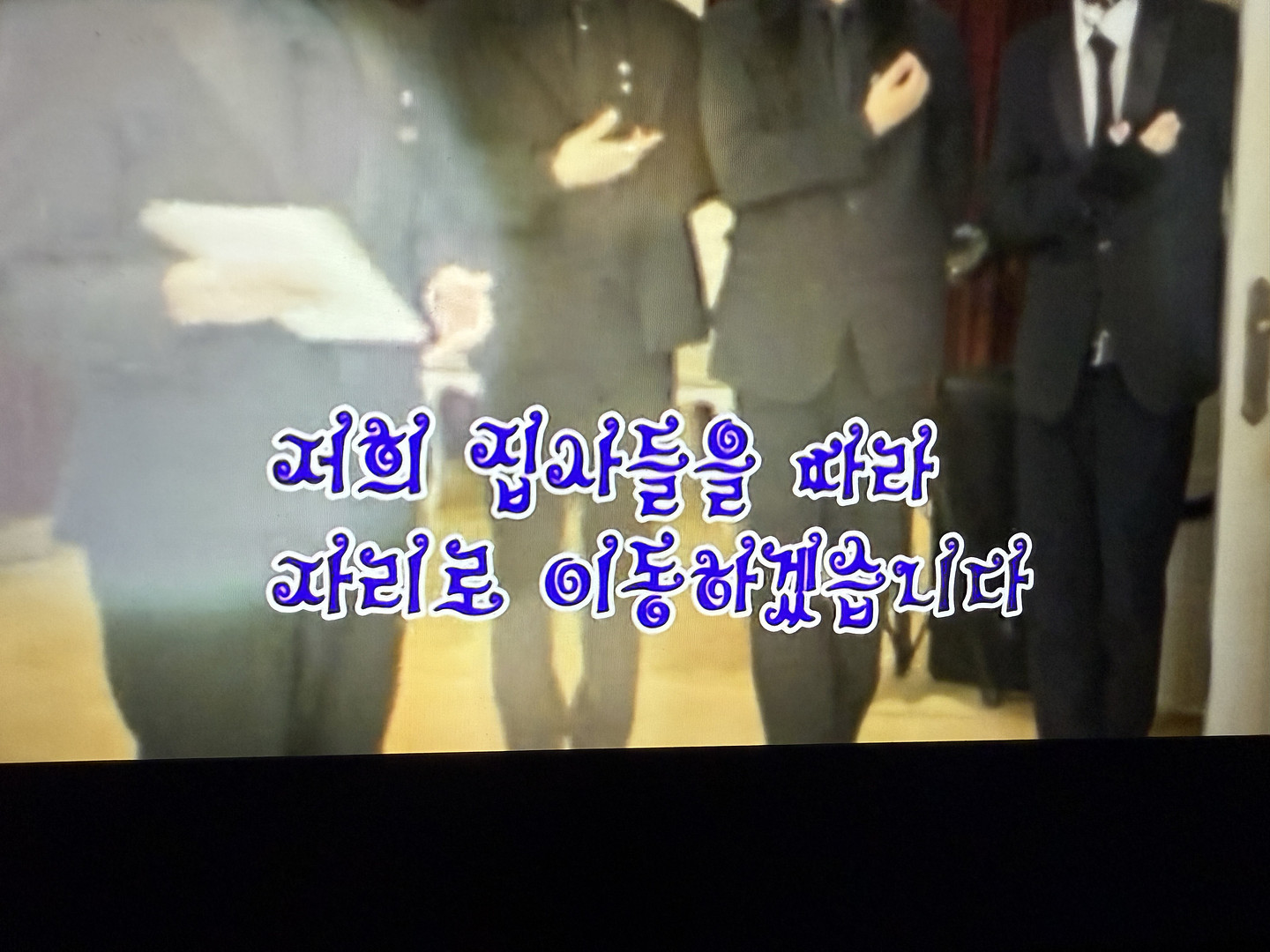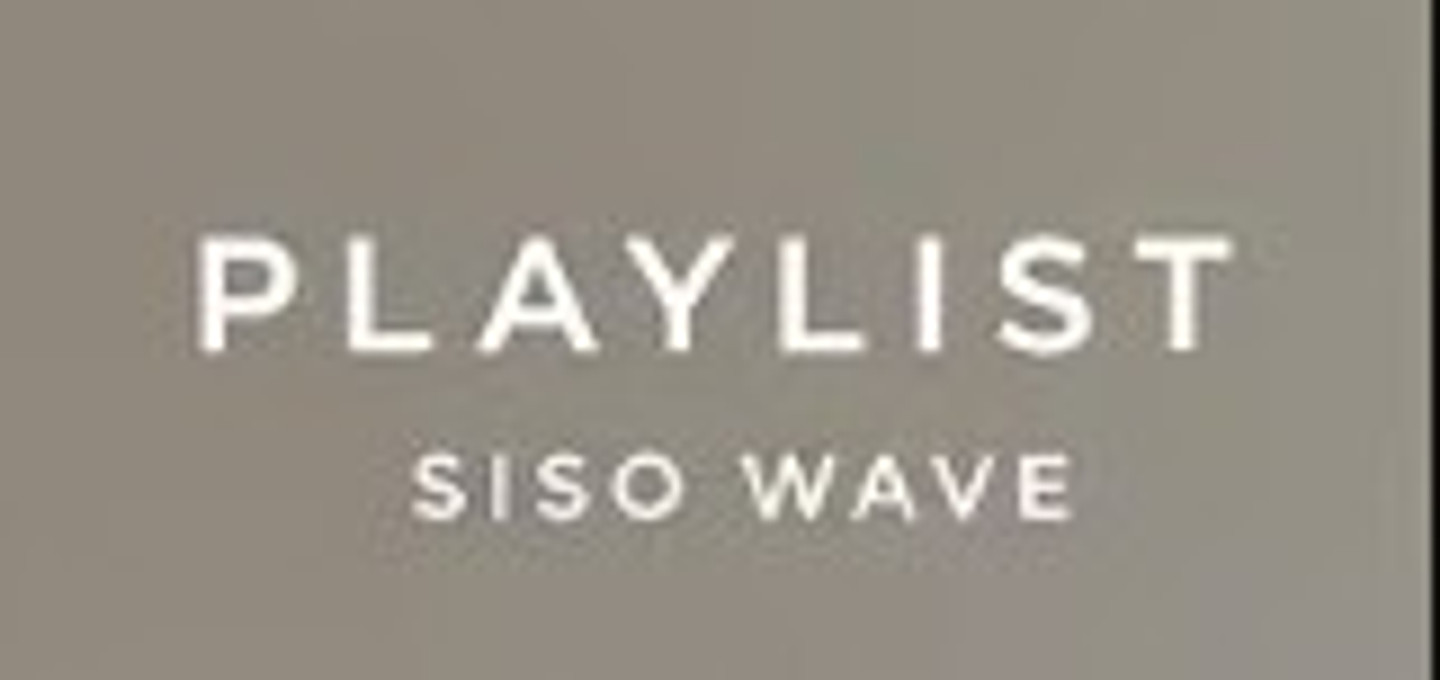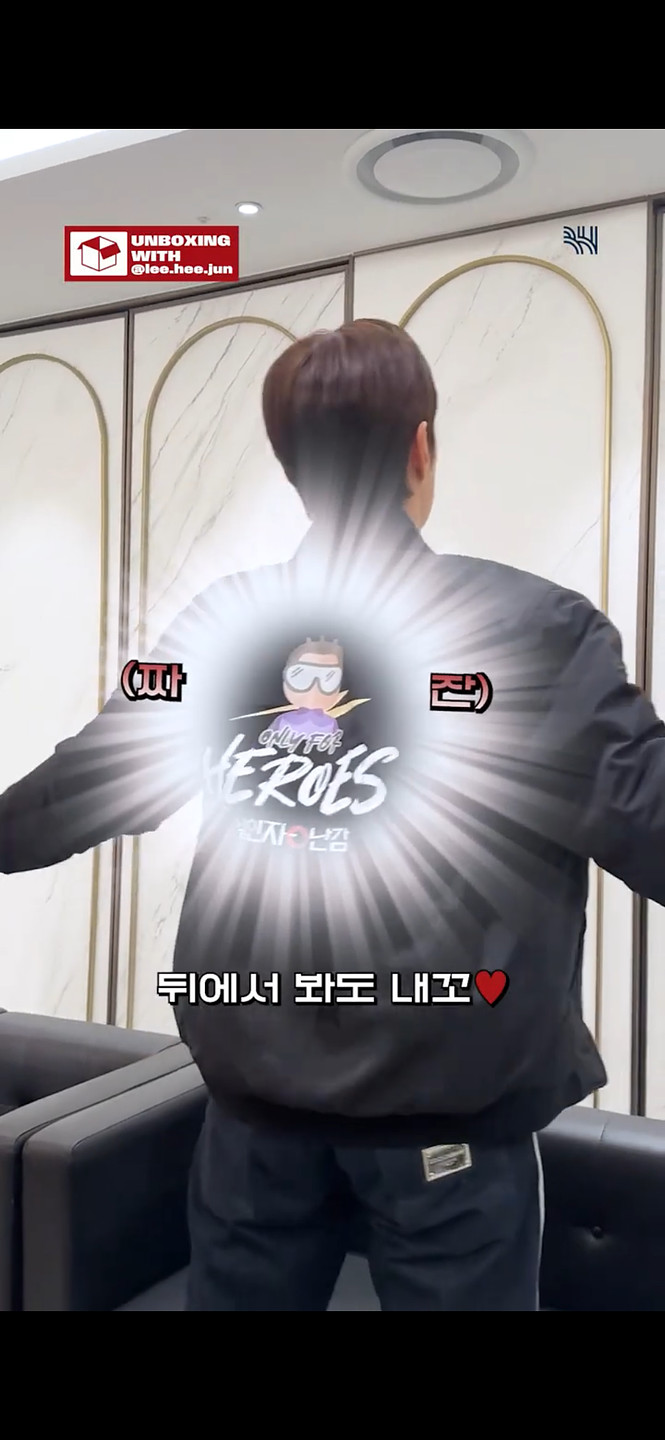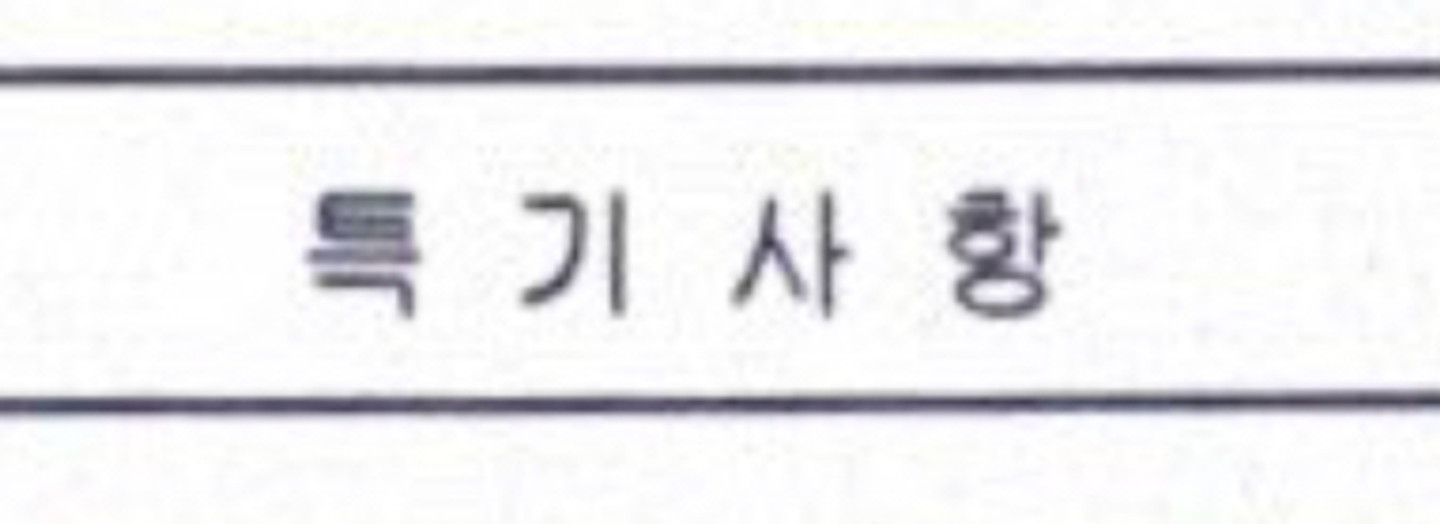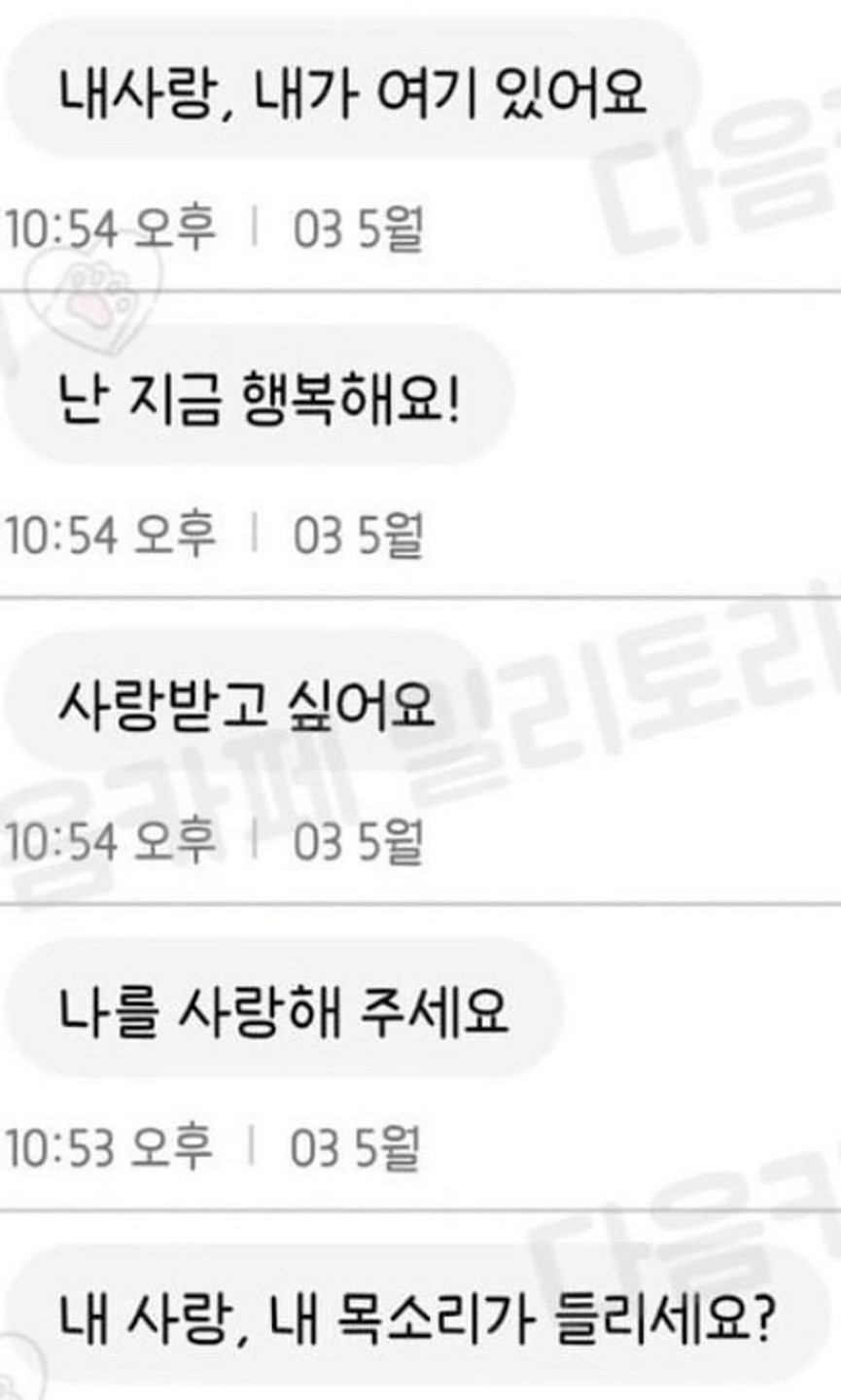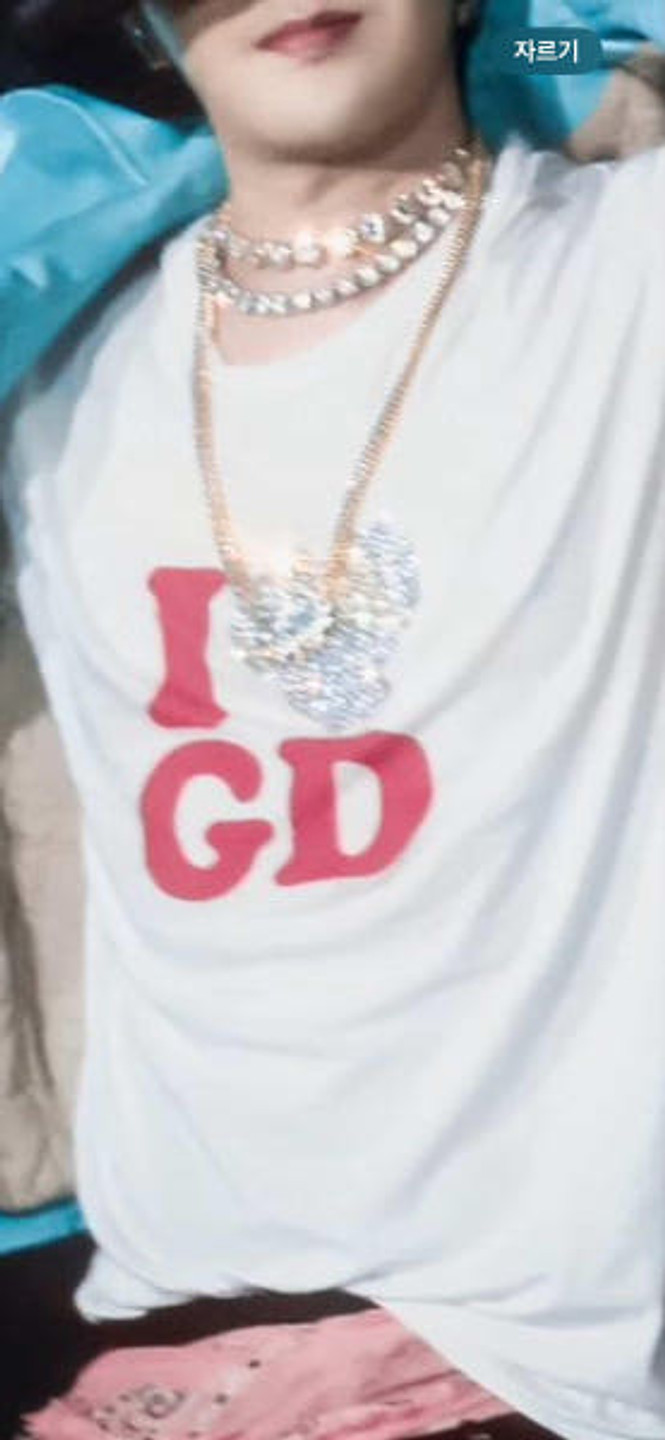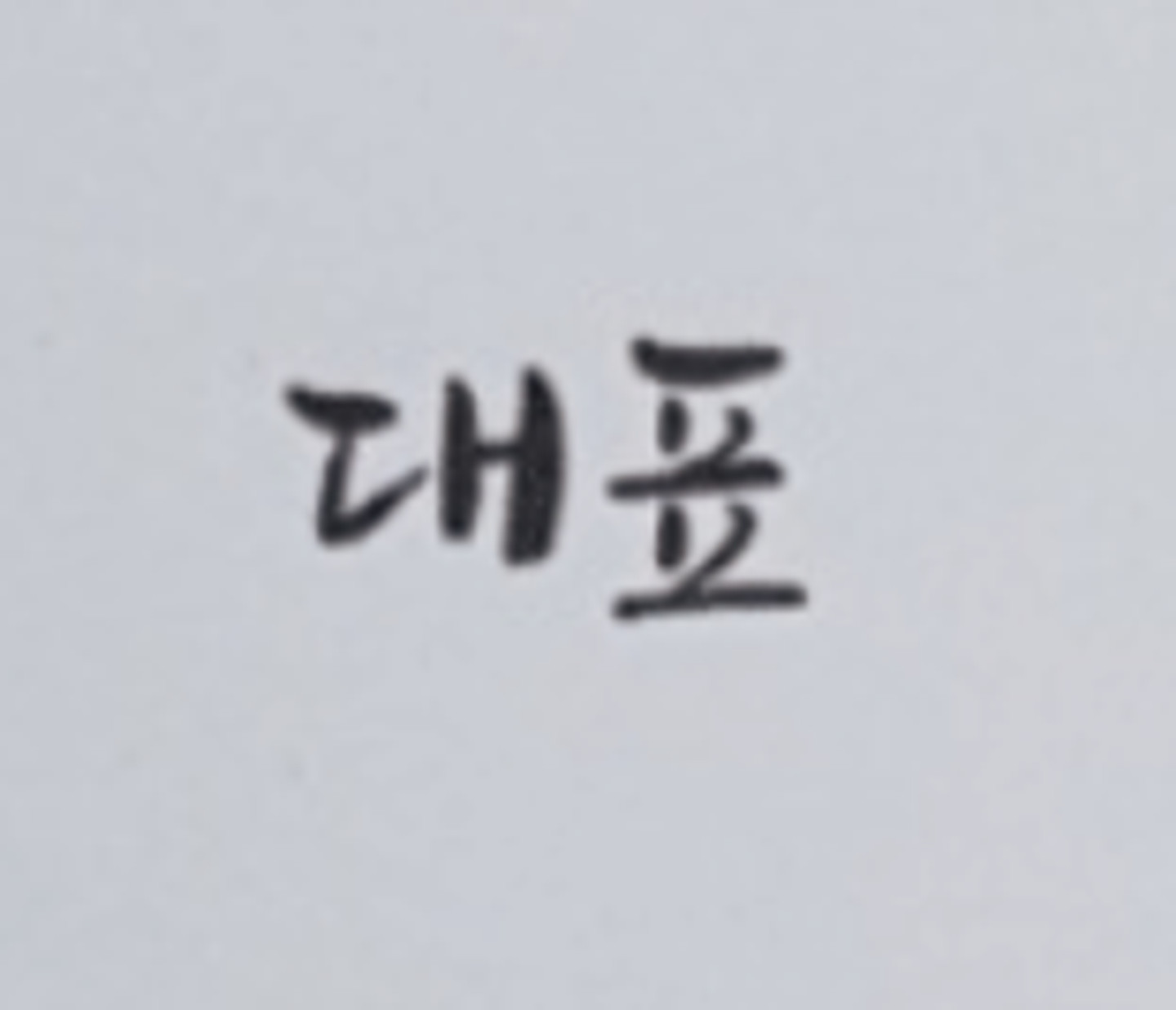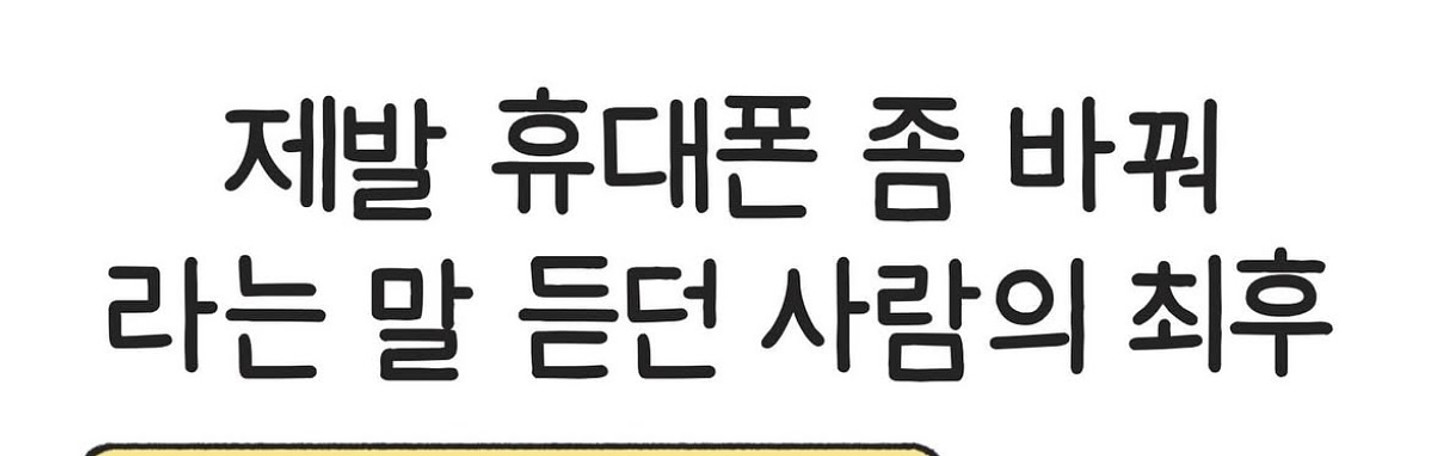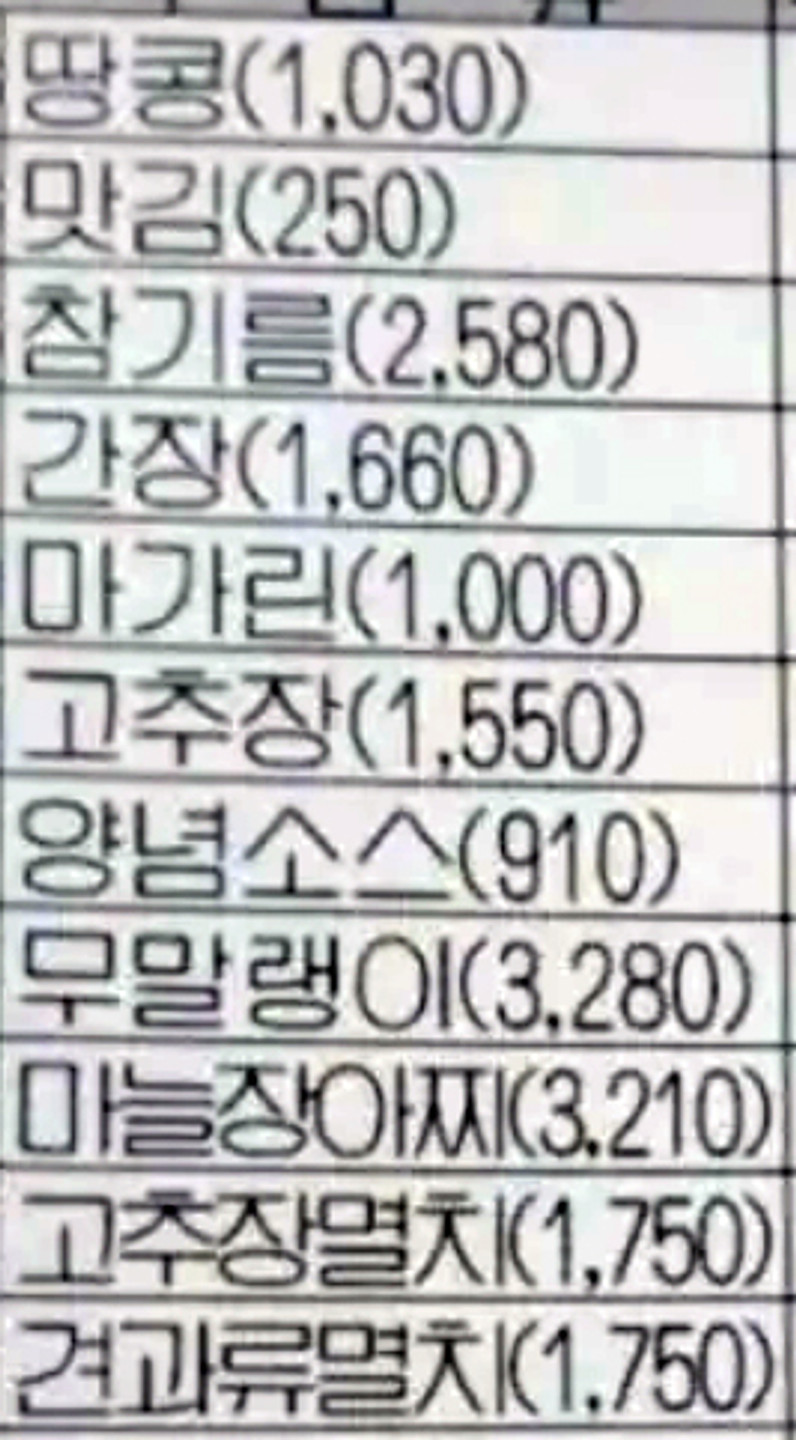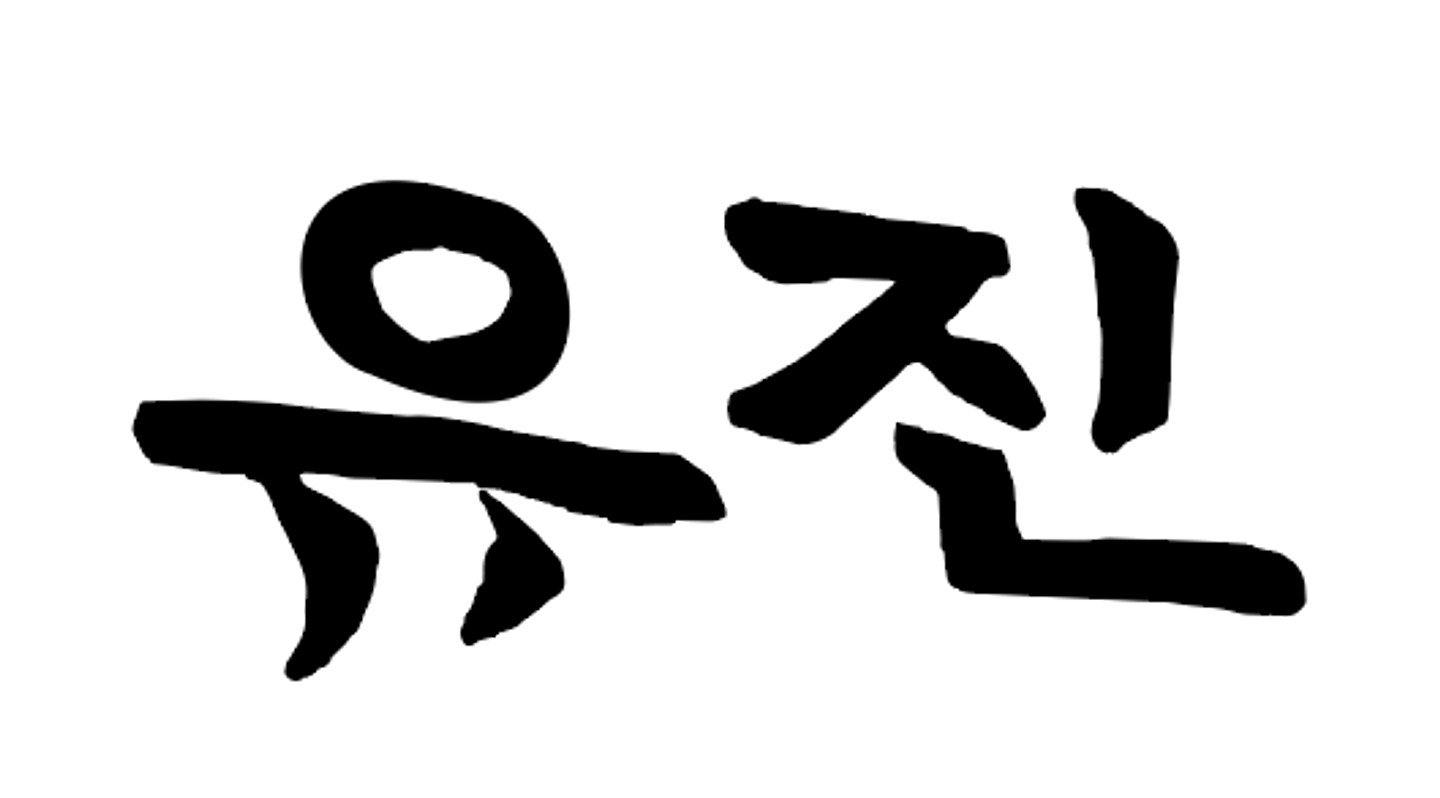
아시는분 계실까요..? 미리 감사합니다!!
안녕하세요. 폰트 이름이 궁금합니다. 도움 주시면 감사하겠습니다.
이 글씨체 아시는 분 있으신가요
이 폰트 뭔가요 ㅜㅜ
전에 쓰던 Aa한나체 였는데 카톡 업뎃하면서 사라졌어요 제일 비슷한거 찾고있습니다 ㅠㅠㅠ 지금 리뉴얼 된 한나체랑 거리가 멀어요
무슨 폰트일까요!?
글씨체 뭘까요?!
어떤 글자체일까요-? 비슷한 글자체라도 알려주세요😭
이 폰트 무엇인지 궁금해요!
이거 폰트 뭘까요?
무슨 폰트일까요? 매우매우 궁금합니다!
폰트이름이 뭔가여?
이 폰트 이름 아시는 분 계시나요? 궁금합니다ㅠㅠ
이 폰트 알려주세영
이 유튜브 자막 폰트 먼가여??
환승연애 지연님 유튜브 자막폰트 먼가여!?!
이 서체도~부탁해요~
이 서체도 부탁드려요
무슨서체일까요?
이 몬치치 폰트 뭔지 궁금합니다
폰트 알려주세옹
폰트 이름이 기억이 안 납니다...ㅠㅠ
이폰트가 궁금합니다 고수님들 부탁드립니다~
이 책에서 나오는 글자 폰트가 뭘까요...?!
무슨 폰트인지 알려주세요
영문 폰트 뭘까요~?
폰트명 알려주세요
이 폰트이름 아시는분? 고수님들의 도움이 필요합니다!
왕과 사는 남자 타이틀 폰트 뭘까요? 비슷한 거라도 알려주세요
폰트체가 뭘까요?
이 글씨에 사용된 폰트가 궁금합니다!! 도와주세요!!!!!
옷에 프린트된 폰트 궁금합니다
이 명조체 뭘까요?
폰트 아시는 분 계신가요
archive 폰트 궁금해요!
제발 찾아주세요 고수님들
‘나례청’이라고 쓰인 부분 무슨 폰트일까요??
이 글씨체 눈누에서 봤던 거 같은데 막상 찾으려 하니 못찾겠네요ㅜㅜ 정보 아시는 분 알려주시면 감사하겠습니다 !!
메인 폰트 뭘까요?
위아래 폰트 둘 다 궁금해요!
폰트 궁금해요!!
아일릿 유튜브에 이거 폰트 뭘까요?
이거 폰트 뭔가요?
헤이유정 유튜브에 나오는 폰트 궁금해요!
폰트명 뭘까요ㅠㅜ
이 폰트 궁금해요
이 폰트 뭔가요
무슨 폰튼지 알 수 있을까요
이 폰트 궁금해요!
이응이 살짝 눌렸어요 캣고딕두번째 폰트랑 비슷한데 살짝 다르네요 ㅜㅜ 뭘까요
안녕하세요 이 폰트가 궁금합니다 ㅠㅠ
폰트 이름 부탁드립니다~
이 폰트 뭔가요??
제발..아는 분 계신가요ㅠㅠ 릴스에 자주 보입니다